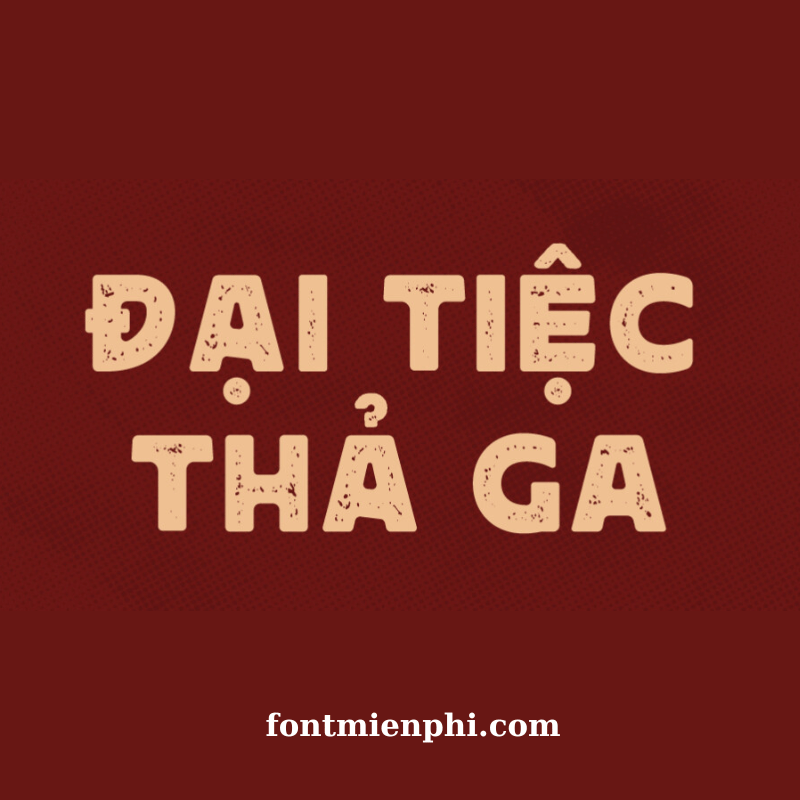
Font Việt hóa 1FTV VIP Rushen Distressed Regular – Phong Cách Độc Đáo Cho Thiết Kế
Giới Thiệu
Font Việt hóa 1FTV VIP Rushen Distressed Regular là một trong những font chữ nghệ thuật được ưa chuộng nhất hiện nay, đặc biệt phù hợp với các thiết kế mang phong cách vintage, grunge hoặc hand-drawn. Với nét chữ cố ý “distressed” (sờn mòn), font chữ này mang đến vẻ đẹp hoài cổ, độc đáo, giúp sản phẩm thiết kế của bạn trở nên ấn tượng và khác biệt.
Đặc Điểm Nổi Bật Font Việt hóa 1FTV VIP Rushen Distressed Regular
- Phong cách độc đáo: Rushen Distressed Regular sở hữu nét chữ không đều, tạo cảm giác thủ công, phù hợp với poster, logo, bìa sách, và các dự án nghệ thuật.
- Hỗ trợ tiếng Việt: Được Việt hóa chuẩn, font chữ đảm bảo hiển thị rõ ràng các ký tự có dấu, phù hợp với mọi dự án trong nước.
- Đa dạng ứng dụng: Thích hợp cho thiết kế in ấn, quảng cáo, thời trang, và cả nội dung digital.
Kết Luận